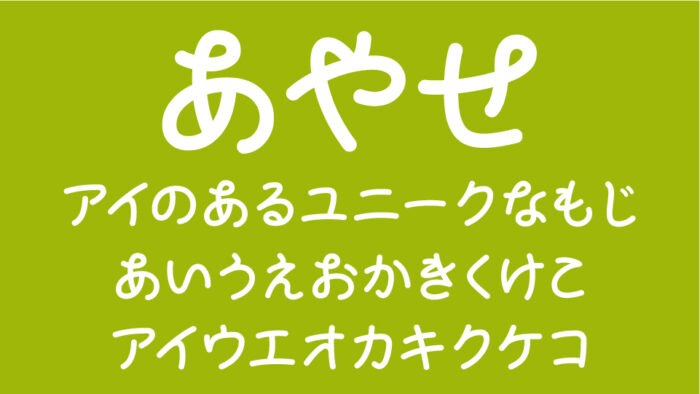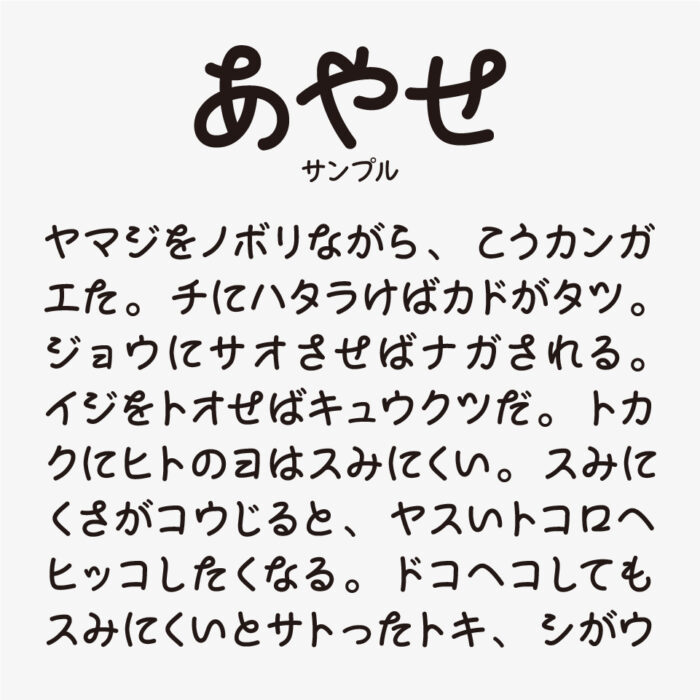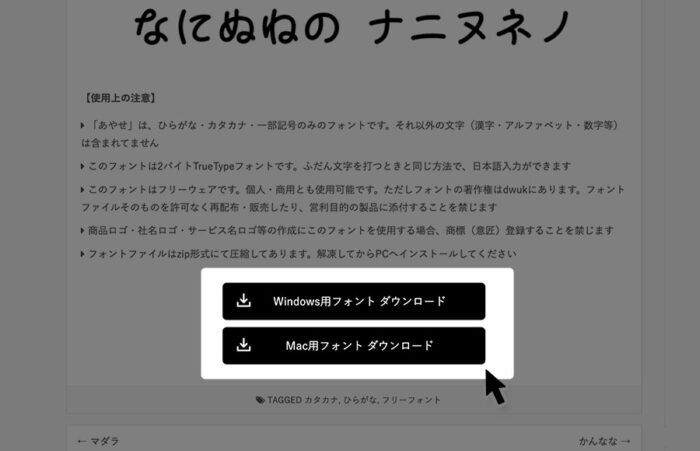
あやせ
あやせフォントは、ゆるく丸みを帯びた文字が特徴で、素朴な温かみと可愛らしさを兼ね備えた手書き風フォントです。
文字の大きさや線の太さにわずかな揺らぎがあり、手書きの筆記のような文字の線のつながりがあるのがアクセントになっており、可愛い雰囲気を感じるフォントです。丸っこい字形ながらもバランスがよく、長文でも視線がスムーズに流れるので、読みにくさも感じないデザインがとってもステキです。